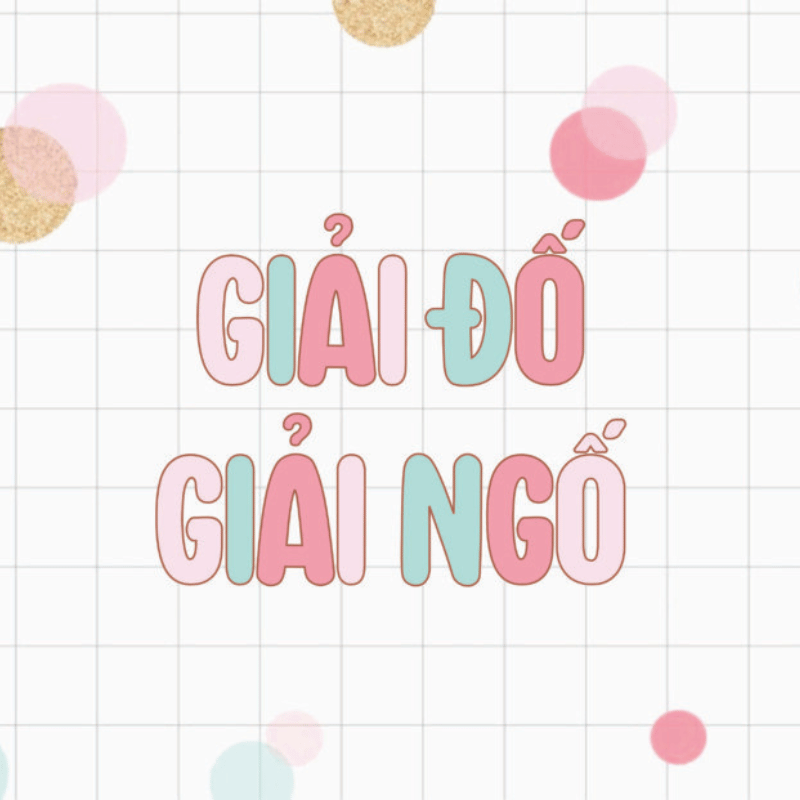
Font Việt hóa VN Positive Sunshine
Font Việt hóa VN Positive Sunshine  – Nét Chữ Tươi Sáng, Đậm Chất Việt
Giới Thiệu
Font Việt hóa VN Positive Sunshine là kiểu chữ độc đáo, được thiết kế dành riêng cho người dùng tiếng Việt. Với phong cách tươi vui, nét chữ mềm mại nhưng không kém phần năng động, font chữ này trở thành lựa chọn hoàn hảo cho thiết kế đồ họa, nhận diện thương hiệu, hoặc các dự án sáng tạo.
Đặc Điểm Nổi Bật
• Hỗ trợ Tiếng Việt: Font bao phủ đầy đủ bảng mã Unicode, hỗ trợ các ký tự có dấu, đảm bảo hiển thị rõ ràng và mượt mà.
• Phong Cách Tươi Sáng: Nét chữ tròn trịa, độ dày vừa phải, mang lại cảm giác thân thiện, phù hợp với thiết kế hướng đến giới trẻ hoặc thương hiệu năng động.
• Đa Dạng Ứng Dụng: Dùng cho poster, logo, bao bì, social media, hoặc tài liệu quảng cáo.
Kết Luận Font Việt hóa VN Positive Sunshine
VN Positive Sunshine không chỉ là font chữ thông thường mà còn là công cụ truyền tải thông điệp tích cực. Nếu bạn đang tìm kiếm một font Việt hóa chất lượng, dễ đọc và giàu tính ứng dụng, đây chính là sự lựa chọn lý tưởng!